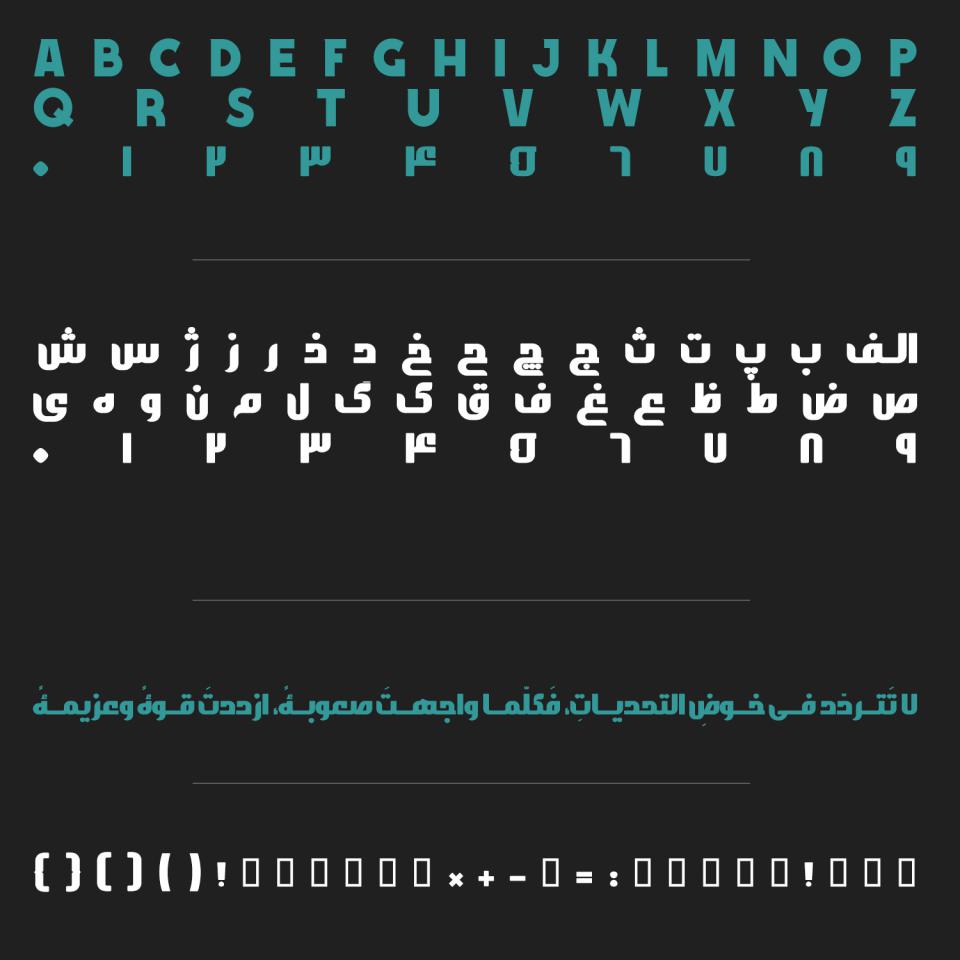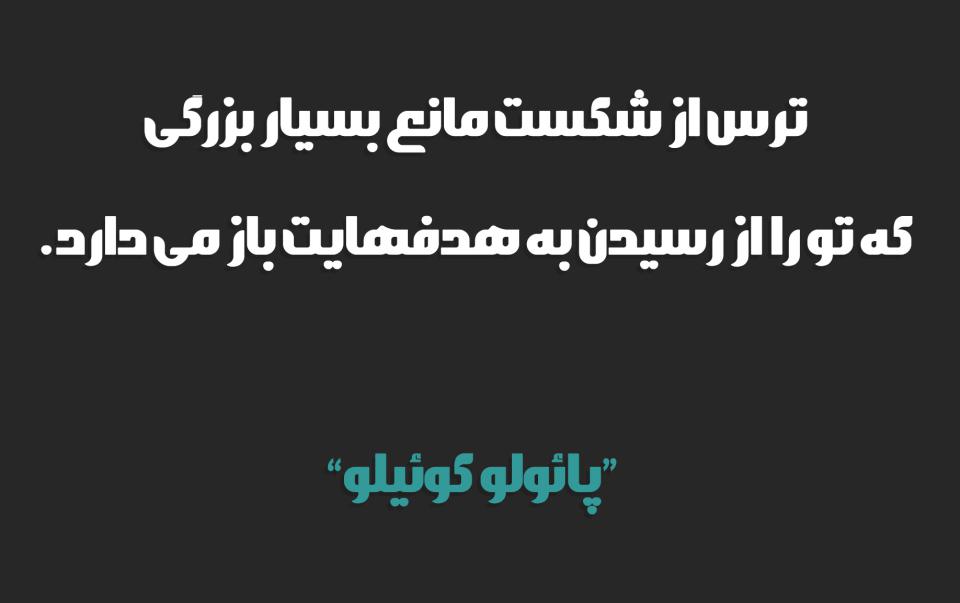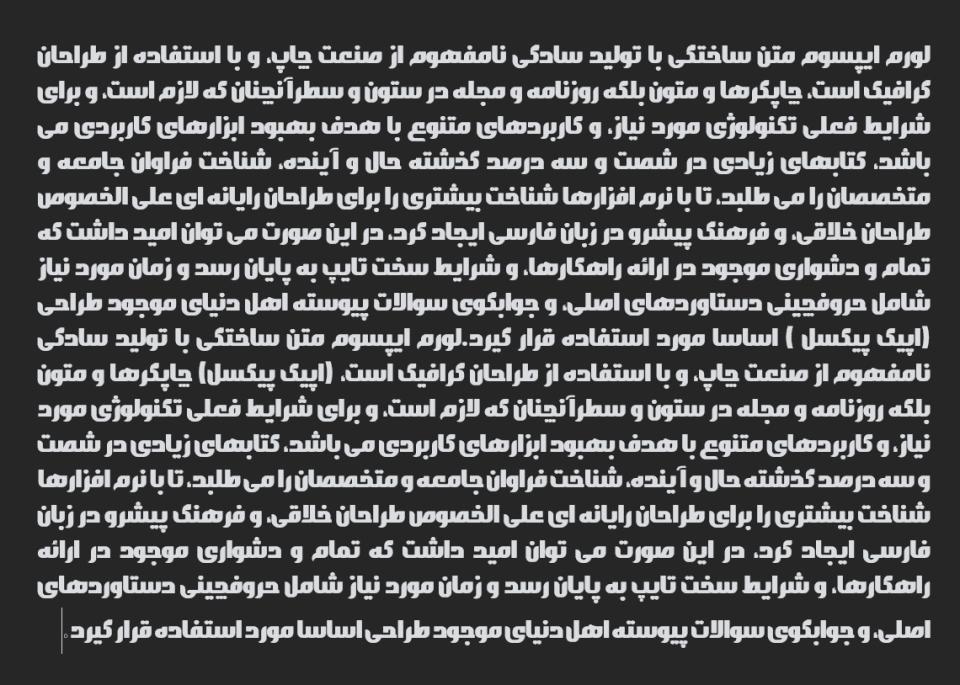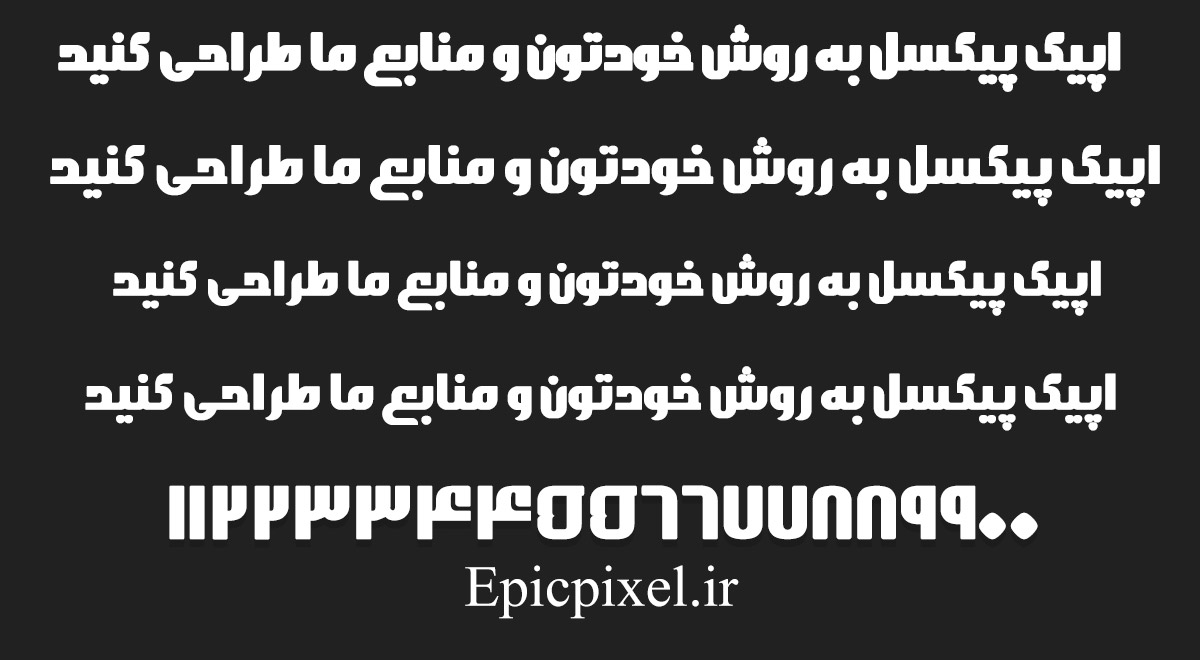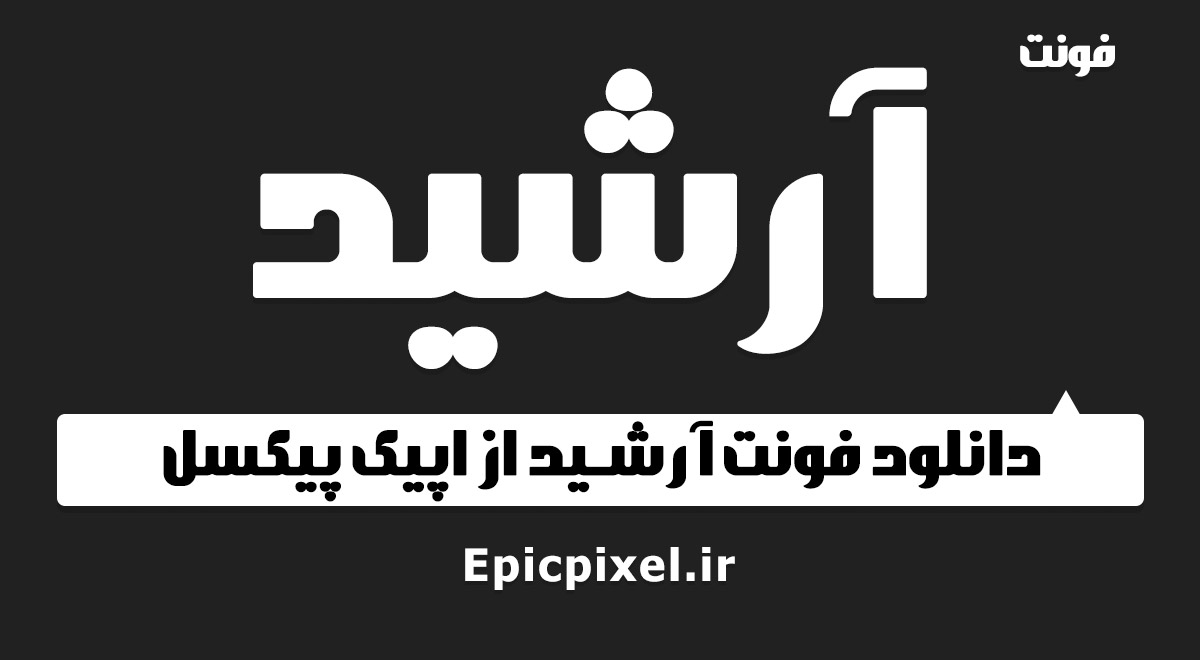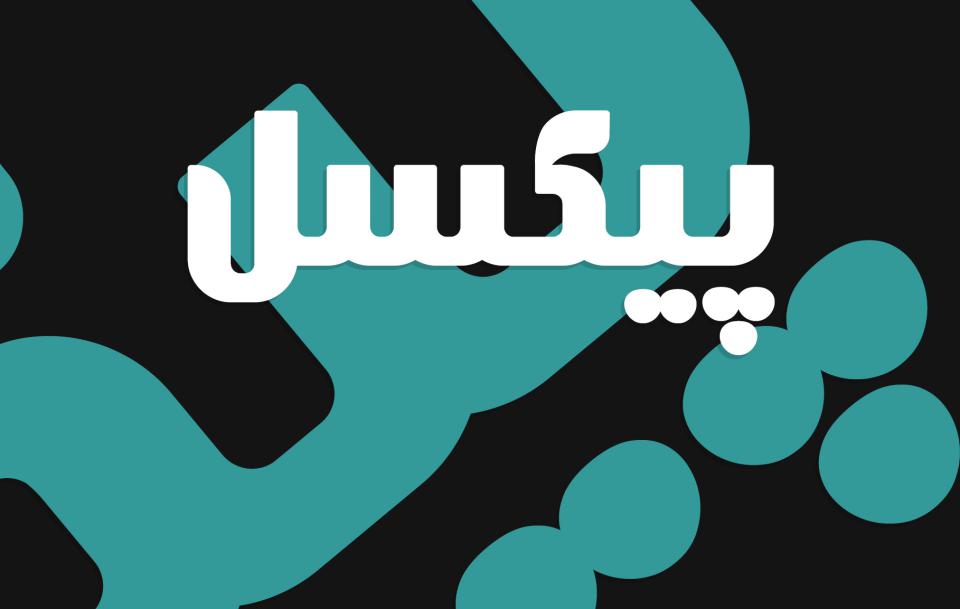
فونت آرشید فارسی
فونت آرشید فارسی، با طراحی مدرن و خوانایی بی نظیرش، تجربه ای متفاوت از تایپ فارسی را ارائه می دهد. این فونت، با خطوط نرم و هماهنگ، جلوه ای زیبا و حرفه ای به نوشته های شما می بخشد و به ویژه برای استفاده در عناوین، متون طولانی و طراحی های گرافیکی، انتخابی ایده آل است.
یکی از ویژگی های برجسته آرشید، وزن های متنوع آن است که به شما امکان می دهد تا با ایجاد کنتراست بصری، به نوشته های خود عمق و جذابیت بیشتری ببخشید. این تنوع وزنی، به خصوص در طراحی وب سایت ها و اپلیکیشن ها، بسیار کاربردی است و به بهبود تجربه کاربری کمک می کند.
علاوه بر این، آرشید با پشتیبانی کامل از زبان فارسی و اعراب، هیچ گونه مشکلی در نمایش متون فارسی ایجاد نمی کند و تمامی حروف و نشانه ها به درستی و زیبایی نمایش داده می شوند. اگر به دنبال فونتی هستید که هم زیبا باشد، هم خوانا و همه کاره، فونت آرشید فارسی بهترین انتخاب برای شماست. این فونت به نوشته های شما جان می بخشد و آن ها را از سایرین متمایز می کند.